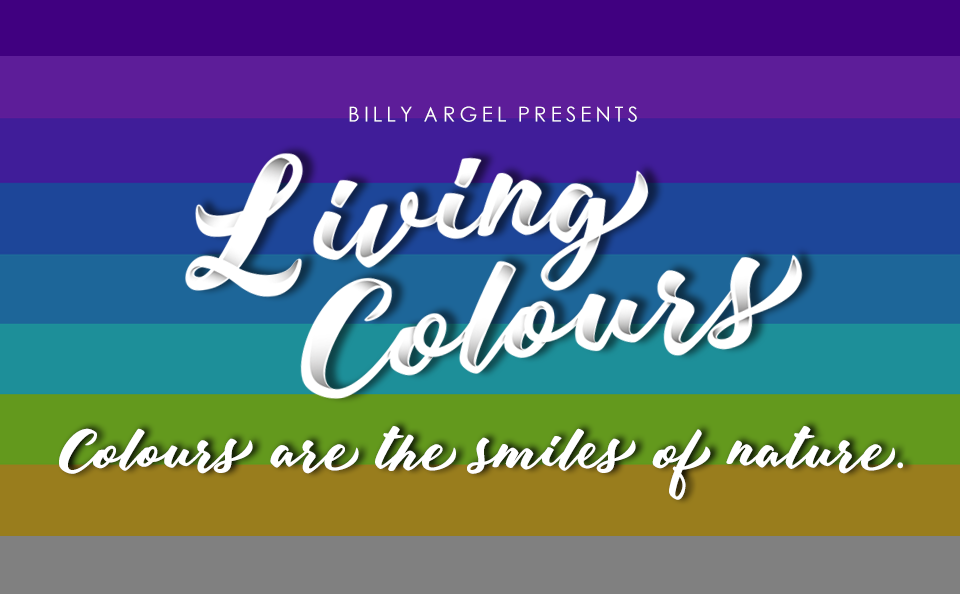
A fonte “Living Colours Script Font” é uma delícia para qualquer projeto que deseje dar vida às palavras com uma escrita elegante e vibrante. Escrevendo em Living Colours Script revelará um estilo único, capaz de enriquecer seu design gráfico de maneiras incríveis. Esta fonte foi criada pelo designer Billy Argel, disponível tanto para uso pessoal quanto comercial. Para quem está interessado em adquirir uma licença comercial ou a completa coleção do script, Billy Argel disponibiliza todas as informações importantes e um contato direto através do site billyargel.com. Para mais detalhes sobre este incrível recurso gráfico e para conhecer ainda mais obras de Billy Argel, não hesite em visitar o seu site oficial e sua página no Facebook. Acesse www.billyargel.com e explore as possibilidades criativas que Living Colours Script oferece.
Designer: Billy Argel